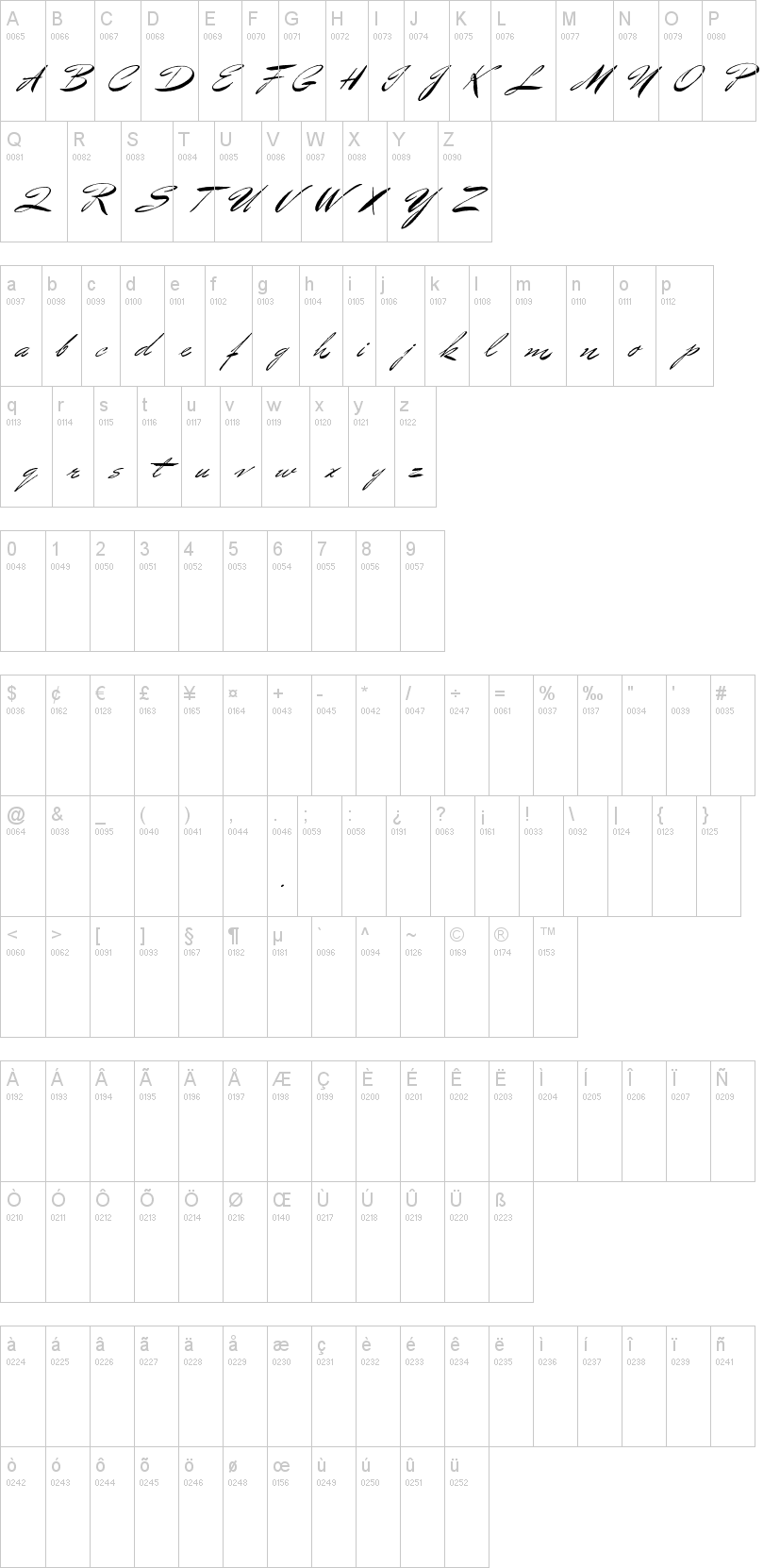
Bluelmin Benedict是一款英文字体,由英国设计师James Puckett于2018年设计。它是一款英式古典风格的字体,具有细腻的线条,优雅的英文字母,精致的圆角,以及较高的可读性。它可以用于印刷品、网页设计、平面设计、logo设计等多种应用场景。内容介绍
Bluelmin Benedict是一款非常不错的手写艺术字体,具有很好的视觉感,适合于文化类的宣传设计、商业类品牌的广告和产品包装设计以及个性化文字排版等较多场景。